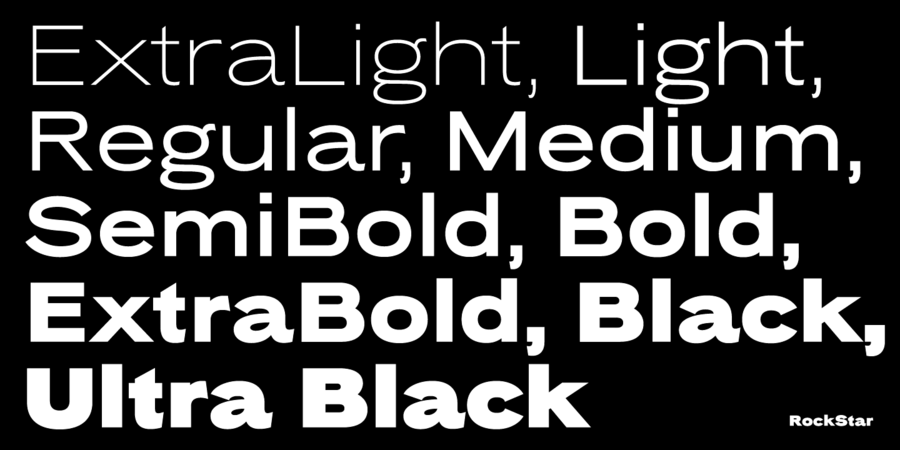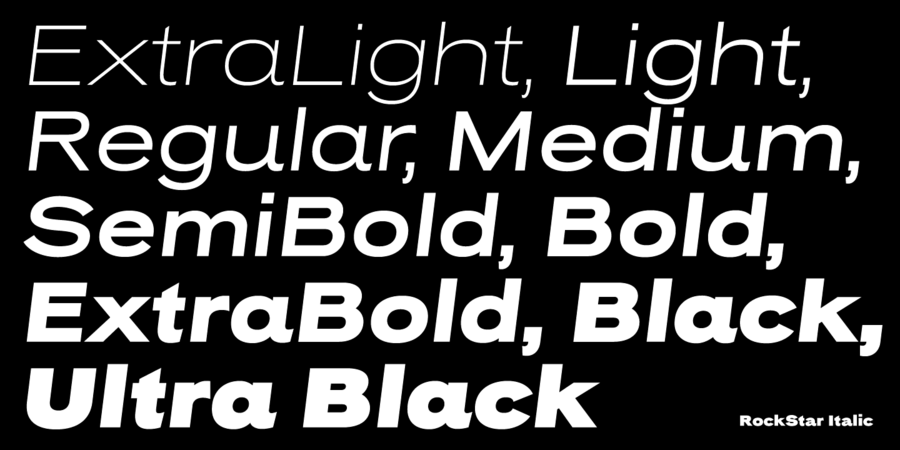
Оригінальне ґротескне шрифтове сімейство з яскраво вираженою індивідуальністю. В гарнітурі 36 накреслень, від Extra Light до Ultra Black у широких і компактних пропорціях (включно з курсивами). Широкий діапазон ваги й ширини, пропонує величезну типографічну гнучкість. Rock Star – це сучасний шрифт, що має коріння в минулому. Він заснований на старих ґротесках кінця 19 і початку 20 століття. Це чудовий вибір для корпоративного брендингу, дизайну книг і журналів. Шрифт розробив Кирило Ткачов у 2020 році.
36 накреслень
Асоціації з сімейством шрифтів Rock StarОсобистість і характер гарнітури:
прозорий, тонкий, легкий, гострий, твердий, гордий, модний, різкий, чіткий, популярний, стійкий, стабільний, якісний, самостійний, західний, рівний, надійний, серйозний, значний, гучний, сміливий, колючий, переконливий, сильний, солідний, крутий, сталевий, залізний, мотивуючий, амбітний, щедрий, важливий, суворий, жорсткий, потужний, яскравий, виразний, зухвалий, грубий, тусовочний, рясний, насичений, нічний, важкий, дзвінкий, помітний, клубний, двіжняковий, ризикований, урбаністичний, агресивний, активний, кричущий, брутальний, екстремальний, нахабний, запальний, чорний, радикальний, худий